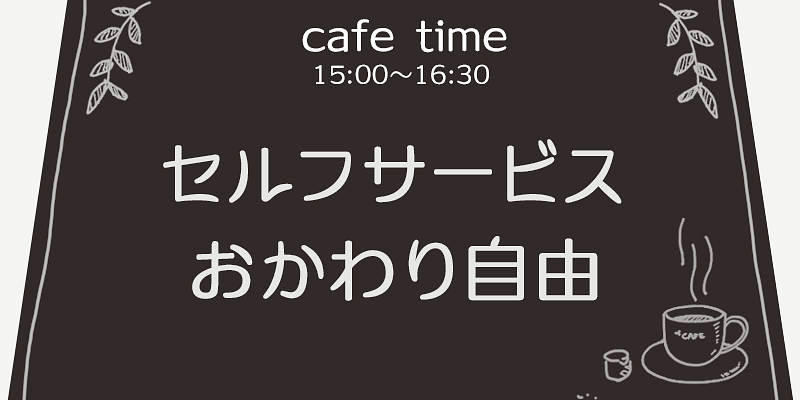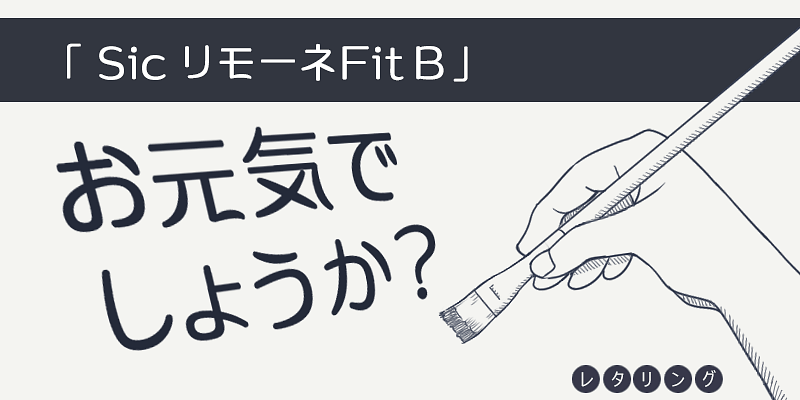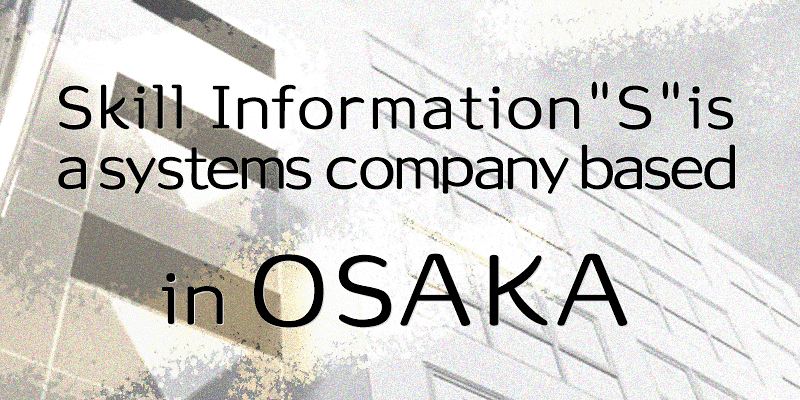
Die von Takeharu Suzuki entworfenen Schriften spiegeln seine umfangreiche Erfahrung im Schrift-Design wider – von Handlettering über Bitmapschriften bis zu Textverarbeitungs- und Pinselschriften. Sein Hauptaugenmerk lag auf der Gestaltung einer leicht lesbaren Frakturschrift für horizontalen Text. Dies führte zur Entwicklung von Meiryo, der Windows-Standardschrift für Japanisch, die beim Lesen angenehm und komfortabel ist.
Seine vielfältigen Schrift-Designs umfassen nicht nur weiche Pinsel- und Grundschriften, sondern auch Fraktur-, Kreativ- und Display-Schriften. Diese eignen sich für zahlreiche Anwendungen, darunter Werbung, Video und digitale Medien. Sie strahlen Authentizität aus und sind überaus beliebt.